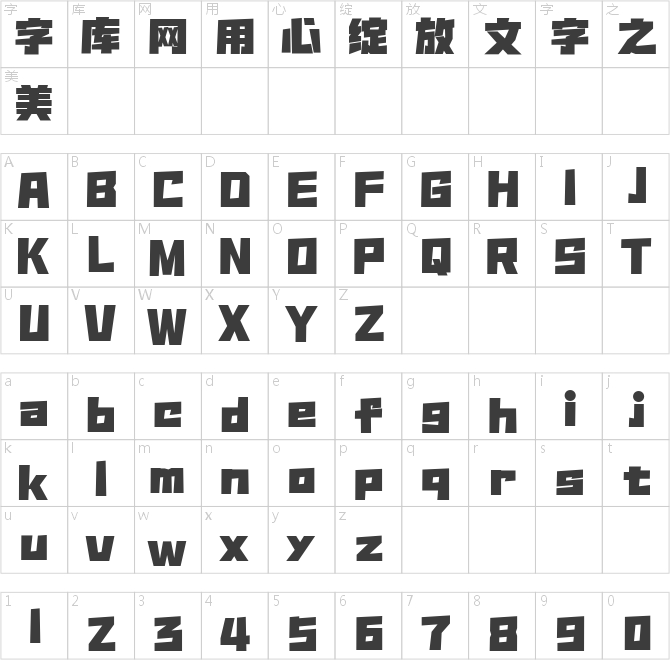
黑體
簡介:一筆壹畫字工坊是一家專注于中文字庫開發的工作室,致力于做大家都用得起的正版字。工作室主創有十年字庫開發經驗,擅長創意、黑體、手寫等市場主流字體。
一筆壹畫潮黑體字體字庫是一款讓人賞心悅目、百看不厭的中文字體,適合各類廣告和產品包裝設計應用,字體大小3.92MB,格式為ttf字體,上傳用戶是一筆壹畫字工坊,作者/版權方為一筆壹畫